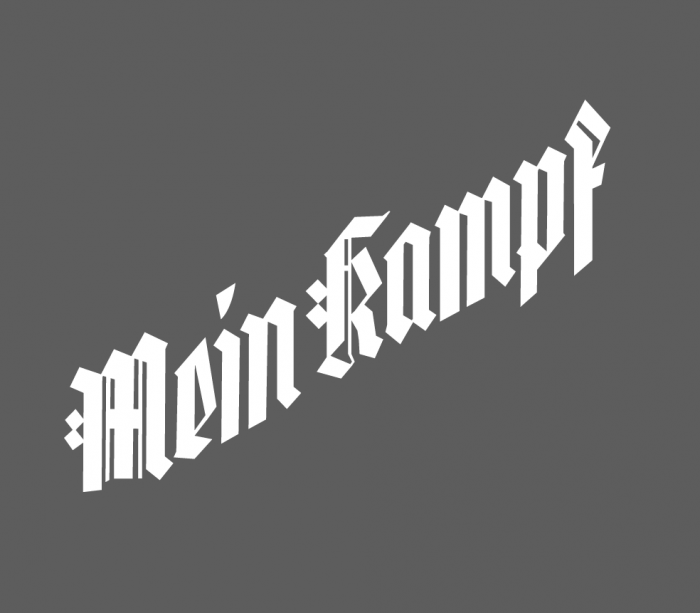
Hitler Mein Kampf Cover
Ich bin auf der Suche nach der exakten Schrift die für diesen Schriftzug verwendet wurde.
klar Fraktur - aber welche?
Fraglich, ob das eine Satzschrift ist, die dort verwendet wurde und noch fraglicher, ob sie heute digitalisiert zur Verfügung steht. Das gesuchte Beispiel ist ja dem Original-Titel des Eher-Verlags entnommen.
Eine Bleisatzschrift kann es nicht gewesen sein, technisch ist das nicht möglich. Wenn man eine Schaftstiefelgrotesk ein bißchen zurechtzerrt, kommt man bestimmt auch zu einem monströsen Ergebnis.